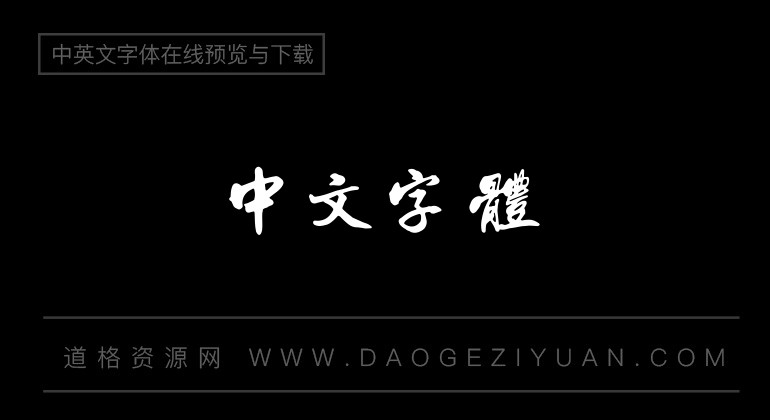
漢鼎繁特行是一款漢字字體,由漢鼎設計公司設計,它是一款繁體字體,採用現代設計理念,結合傳統漢字文化,融入現代形態,創造出一種全新的漢字字體。漢鼎繁特行字體細膩、精細,筆劃清晰,讓漢字表達更加精確,更能體現出漢字的精髓。內容介紹
是一款非常不錯的手寫藝術字體,具有很好的視覺感,適合於文化類的宣傳設計、商業類品牌的廣告和產品包裝設計以及個性化文字排版等較多場景。